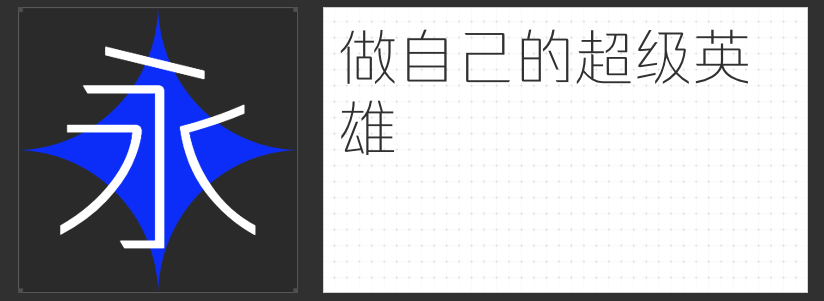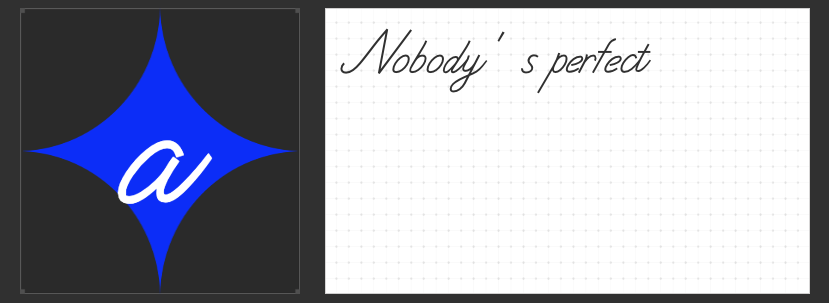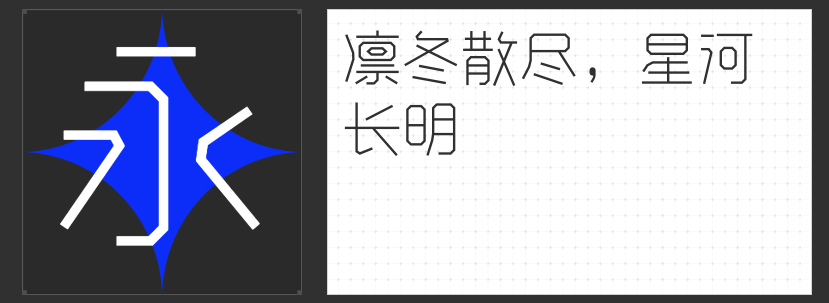
极简风设计轻松拿捏!四款笔画纤细字体推荐
在追求极简风格的设计中,字体的选择至关重要。一款合适的字体不仅能够提升整体设计的质感,还能更好地传达信息。今天,将为大家推荐四款笔画纤细、极简风格的字体。
这款字体以特细的笔画作为字重选择,设计严谨、字态流畅,是一款典型的黑体字。它的中宫匀称,笔画清爽,极具通用性,无论是用于标题还是正文,都能展现出一种简洁明了的美感。
这款字体是一款直线字体,中宫略大,布白均匀,重心统一。它的笔画设计无过多装饰,横竖笔画视觉等粗,笔画多变灵活,以连笔折笔为特色。整体做切口处理,优化尖锐部分,视觉秩序感强烈。无论是中文还是西文符号,都沿袭了相同的设计特点,使得整体风格更加统一。
3.励字细圆简繁
这款字体粗细适中,比黑体更细,清瘦纤细,没有衬线装饰,字面呈正方形。它的笔画横平竖直,全部一样纤细,结构醒目严密,一笔一画都能清晰展现。无论是撇捺等笔画,都处理得圆润而不尖,字形端庄大方,非常适合用于需要精细呈现的设计中。
这是一款西文字体,没有中文字符,但它的笔画线条流畅不拘泥于固定结构,自然随意,极具极简风格。它的设计简洁明了,无论是用于标题、正文还是其他设计元素,都能展现出一种优雅而自然的美感。
以上就是我为大家推荐的四款笔画纤细、极具极简风格的字体。它们各具特色,能够满足不同设计需求。希望这些字体能够为您的设计作品增添一份独特的魅力!